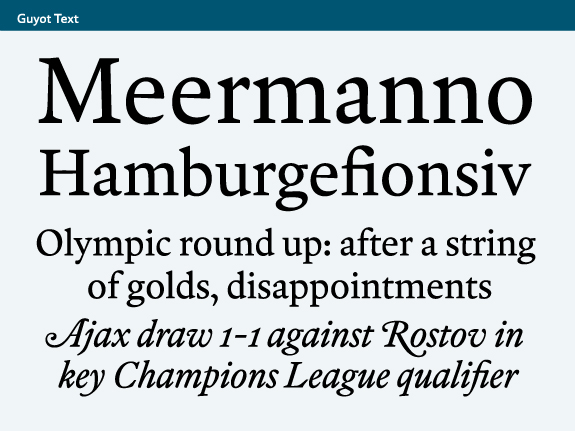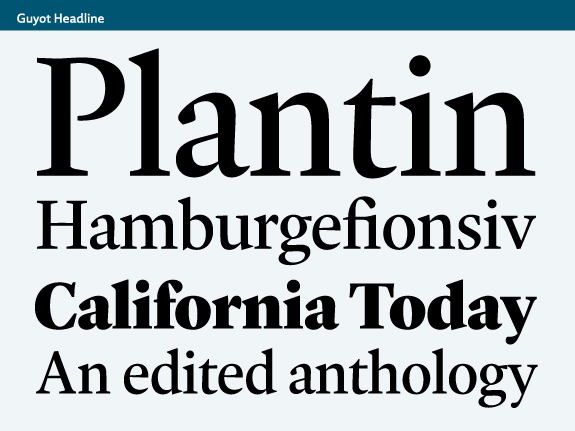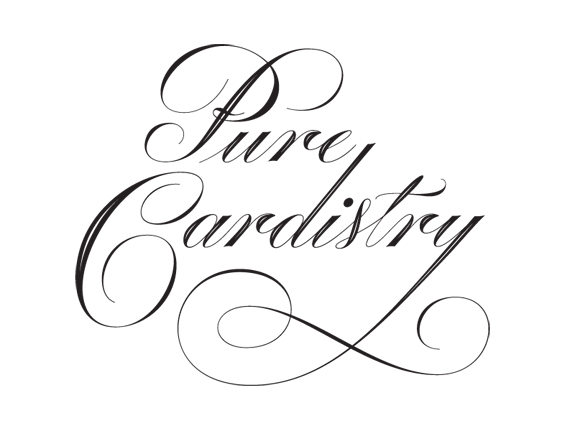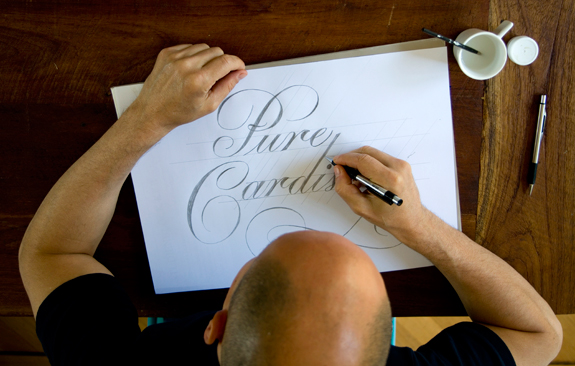
| ¿Qué etapa es la que más te gusta de crear una tipografía? |
Depende un poco de las características de cada proyecto. En ocasiones es muy grata la etapa de investigación, porque visito bibliotecas y descubro detalles en libros antiguos. Siempre se aprende mucho tomando contacto directo con las fuentes e indagando en archivos históricos. En otras oportunidades disfruto con la etapa de bocetado y dibujos. De lo que si estoy seguro es que la etapa del kerning es la que menos disfruto. Es algo muy tedioso y relativamente lento que todo el mundo metido en el diseño de tipos odia hacer.
| ¿Cómo es un día de trabajo para vos? |
No es demasiado diferente al de los diseñadores gráficos independientes, pero hay mucha menos interacción con clientes. Me levanto relativamente temprano y trabajo alrededor de unas 11 horas al día, tomando más café del que debería. Es un trabajo bastante solitario y puede parecer sacrificado, pero disfruto de la rutina haciendo cosas que me gustan y escuchando música. Las distracciones a menudo son el principal enemigo y hay que aprender a no prestarle demasiada atención a las redes sociales o a los emails sin importancia.
| ¿Cuál es tu metodología? |
No tengo un método fijo y lo que vaya a utilizar también depende un poco de cada proyecto; si se trata de un diseño completamente propio, de un revival o si las formas están inspiradas en la caligrafía. Intento que exista una etapa manual en los comienzos porque creo que de esa manera pueden lograrse algunas formas algo más complejas que las que habitualmente se logran siguiendo la mecánica de los contornos Beziér.
En ocasiones, luego de semanas de estas trabajando con contornos digitales, a veces vuelvo a corregir o bocetar en papel para corregir determinados contornos que son difíciles de resolver con la computadora.
| ¿Qué le recomendarías a un estudiante que está en la universidad? |
A quienes les guste mucho la tipografía y deseen profesionalizarse en ese campo, les recomiendo que hagan lo posible por aprender de los mejores maestros a los que puedan acceder. El diseño de tipos y la tipografía de calidad no son disciplinas fáciles. Se requiere un buen conocimiento de la historia del libro, buenas nociones de historia del arte y también el desarrollo de habilidades manuales. Es un poco comparable a aprender a tocar un instrumento. No es algo fácil y para hacerlo profesionalmente, hay que adquirir destreza y profesionalismo de acuerdo a estándares internacionales. Esto es importante porque el mercado de la tipografía es internacional. De nada sirve ser el mejor diseñador de tipos de tu ciudad. Para poder hacer una carrera en esta disciplina es necesario que existan clientes que valoren tu trabajo en un contexto global y para eso se necesita un buen caudal de autocrítica para poder corregir errores propios y luego practicar mucho para poder adquirir destreza.
Para entender la tipografía seriamente hay que conocer bien la historia del libro y contextos históricos tales como los conflictos religiosos Europeos y el rol de los gremios de artesanos.